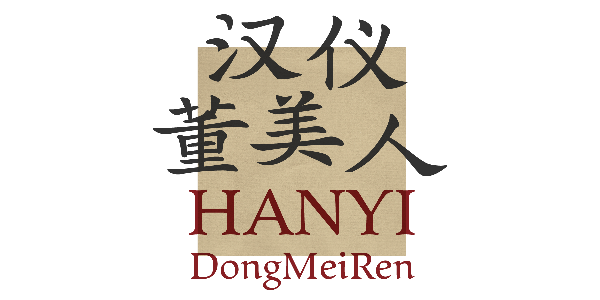
源于隋代碑刻的温婉刻本字体
汉仪唐美人,灵感源于隋代碑刻《董美人墓志》。隋代书法,上承北魏书体,下开唐朝新风,是南北朝到唐之间的津梁,而此碑属上品佳作,堪称隋志小楷第一。字形扁而舒展,取横势,结体严谨稳定,蕴含书写味道的笔画清丽婉转,精劲含蓄。西文部分源于人文主义小写体,保留西文书写的特征,变笔尖书写角度、加入转笔的动作,让入笔出笔变粗,与中文部分相呼应。这款字体具有中式古典气质,优雅、温婉,适用于较短段落文本和副标题的排版,与新中式风格、传统文化主题等使用场景十分契合。
隋代统一天下后,南北方楷书风格融合成隋代书法,《董美人墓志》属其间的上品佳作。它是隋文帝杨坚之子、蜀王杨秀王妃的墓志,由于是皇家墓志,此碑由顶级书家和刻工共同完成,被誉为“隋志小楷第一”。
汉仪董美人以隋代碑刻《董美人墓志》为灵感,是一款清雅婉丽的书法风格设计字体。字形扁而舒展,取横势。习《董美人墓志》清劲潇洒,笔画四面开张,中宫稍紧而不逼仄。
笔画清丽婉转,精劲含蓄,处理精到。形态多姿,用笔方圆兼备,整体彰显华美内敛的气象。并且略带几分行书笔意,书写感强。
汉仪董美人的西文部分源于西文书法中人文主义风格小写体,保留西文书写的特征。为与中文字形更加匹配,西文设计进行扁化处理,改变笔尖书写角度、加入转笔的动作,让入笔出笔变粗,整体更显圆柔顺滑。
汉仪董美人具有中式古典气质,优雅、温婉,适用于较短段落文本和副标题的排版,与新中式风格、传统文化主题等使用场景十分契合。